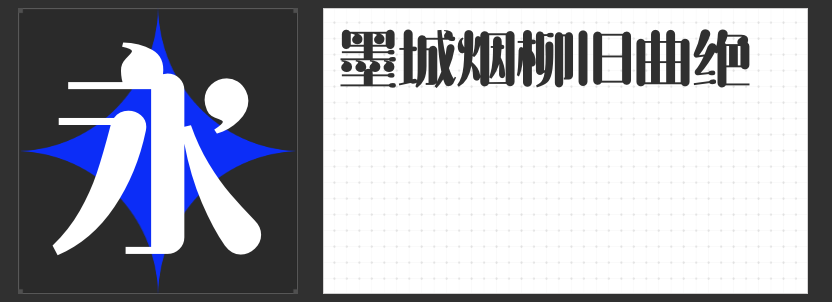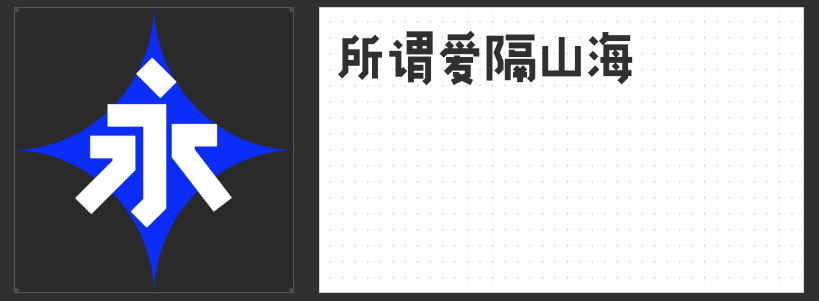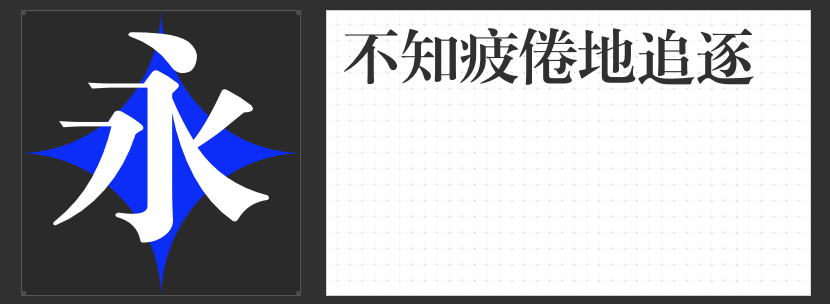
短视频设计字体推荐:四款风格化字体解锁视觉创意新维度
短视频的视觉表达中,字体不仅是信息传递的载体,更是营造氛围、强化风格的关键元素。以下四款各具特色的字体,凭借独特的设计语言与视觉张力,为短视频设计注入鲜活生命力。
一、励字明姿简
这款字体以几何图形为灵感,将圆润的笔画与竖粗横细的对比巧妙结合,形成如同魔法棒挥舞般的灵动韵律。其流畅的弧线与均衡的视觉重心,尤其适合节日庆典类短视频的标题设计,无论是春节的喜庆、圣诞的温馨,还是儿童节的欢快,都能通过字体的形态传递出轻盈跃动的情绪,成为画面中的点睛之笔。
二、励字小标宋简
作为宋体字的创新演绎,它保留了横细竖粗的经典特征,却以更清秀的笔触与严谨的结构打破传统宋体的刻板印象。字体端正而不失雅致,适用于需要传递文化底蕴或正式感的短视频场景,如历史科普、人文纪录片或高端品牌宣传。其适中的笔画粗细变化,既能保证远距离识别度,又能通过细节处理提升画面精致感。
三、励字趣黑简繁
通过断开笔画、棱角折起等创意设计,这款黑体字突破了常规字体的沉闷感。错落有致的字号搭配与活泼的间距处理,赋予文字如同卡通形象般的可爱气质。它尤其适合年轻化、娱乐向的短视频内容,如萌宠视频、搞笑段子或儿童教育类内容,能瞬间拉近与观众的距离,营造轻松愉悦的观看体验。
四、励字光明简 超黑
以ExtraBold的粗壮笔画与饱满字形构建出强烈的视觉冲击力,弧线与斜切笔画的结合既保留了易读性,又增添了锐利感。这款字体是运动、科技、励志类短视频标题的理想选择,其高字宫与开阔字心设计,即使拉伸变形也能保持结构稳定,轻松驾驭全屏展示或动态特效,传递出坚定、进取的视觉语言。